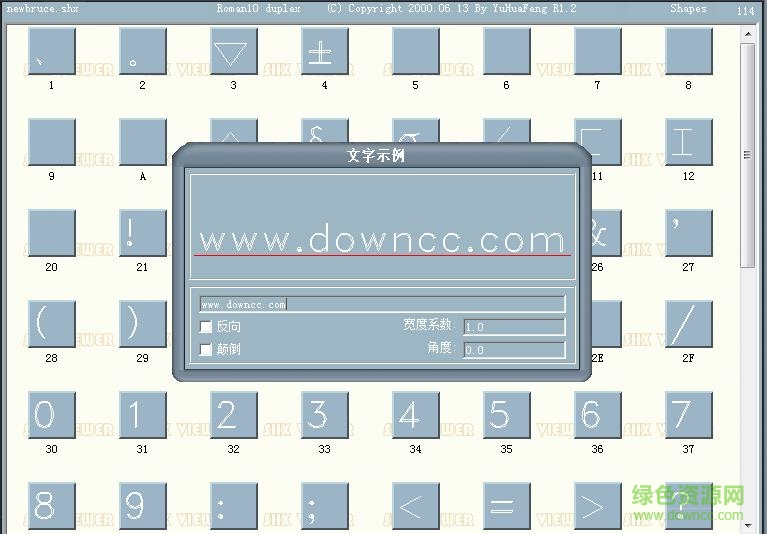
1、表示各種鋼筋符號,不僅采用%%130~133的方法(其順序與其它主流CAD軟件的字體兼容,可以直接代換),還采用了字符替代,直接用$&`^代換I~IV級鋼筋符號($-,&-,`-,^-)。
3、形字體(SHX)的特點(diǎn):
在刷新視圖或平移文字時(shí),屏幕顯示速度更快。
由線條組成的空心字體,結(jié)構(gòu)十分簡單,占用儲存空間小。